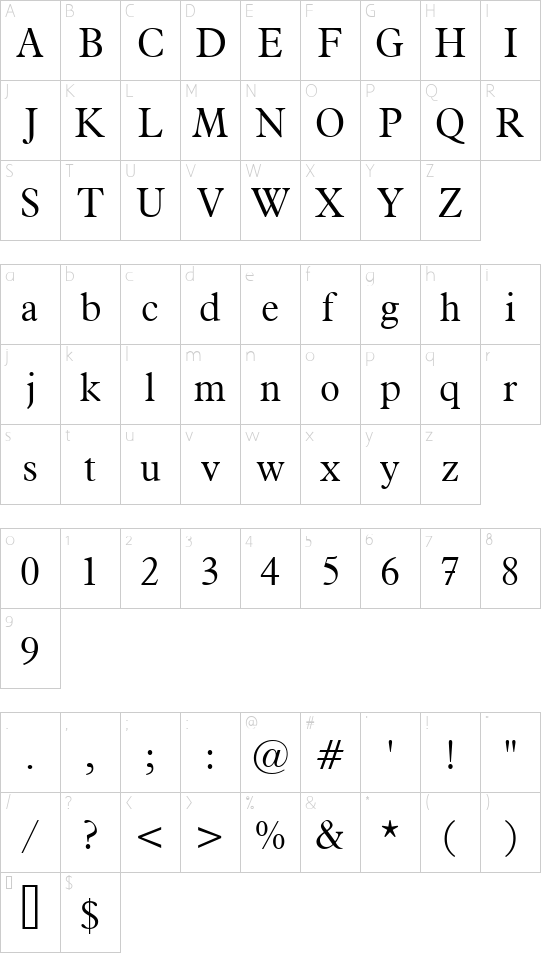
Font UVN Anh Hai Việt Hóa
Tác giả: UVN Anh Hai
Phân loại: Cá tính, Độc đáo
Kiểu chữ: Có chân
Font UVN Anh Hai Việt Hóa là một font chữ có chân cá tính, thuộc bộ font UVN. Được thiết kế với mục tiêu mang lại sự độc đáo và sáng tạo, font này lý tưởng cho các dự án thiết kế như logo, poster, và bao bì sản phẩm. Với các nét chữ sắc nét và độ dày đều đặn, Font UVN Anh Hai Việt Hóa không chỉ dễ đọc mà còn tạo cảm giác hiện đại và phá cách. Việc Việt hóa font giúp người dùng dễ dàng sử dụng trong các thiết kế tiếng Việt, mang lại sự tiện lợi và thẩm mỹ cao.
Font UVN Anh Hai